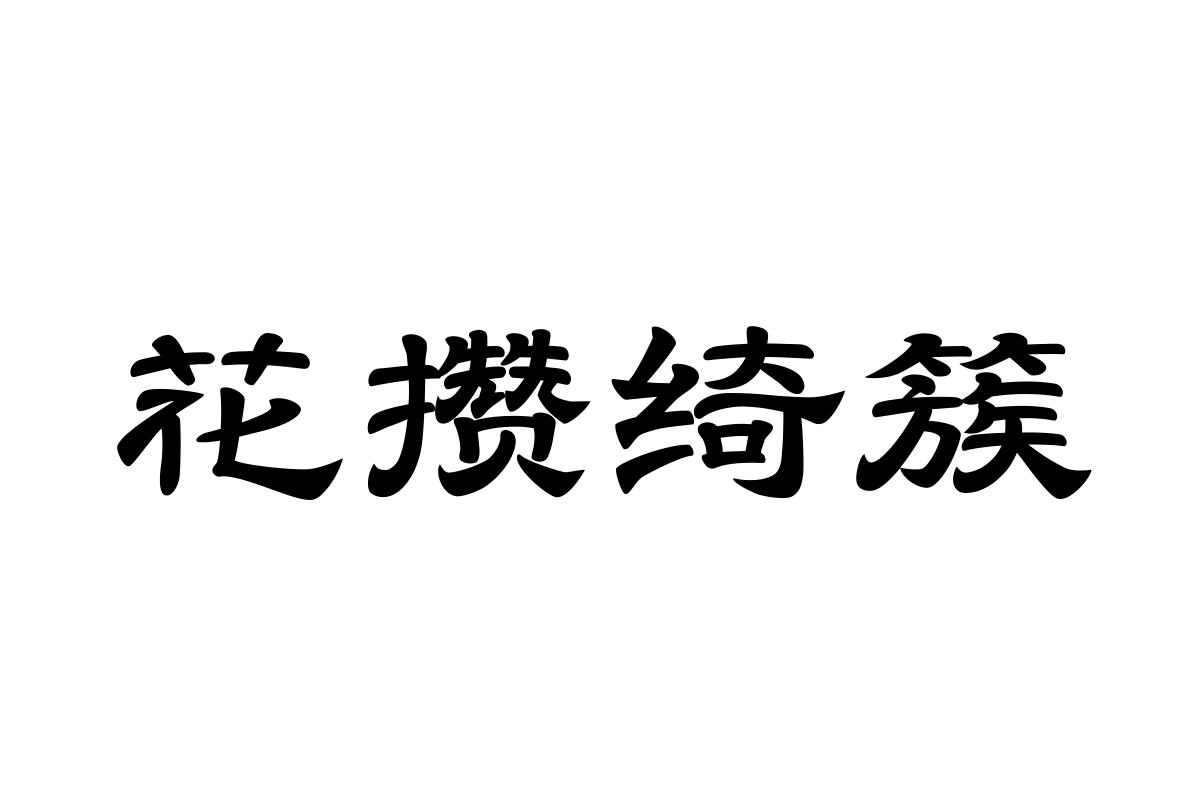
汉仪润隶是一款具有现代感和优雅风格的中文字体,它以圆润的笔画、清晰的结构以及丰富的细节表现而著称。这款字体适合用于需要强调文字美感和艺术气息的设计项目,如广告、包装、杂志、网页等。
汉仪润隶的特点包括:
1. 圆润的笔画:汉仪润隶的笔画呈现出一种柔和的弧度,使得文字看起来更加亲切和易于阅读。
2. 清晰的结构:该字体的结构严谨,每个字符都保持了良好的比例和平衡,使得整体设计看起来和谐统一。
3. 丰富的细节:汉仪润隶在细节上做了充分的处理,如字框、笔画连接处等都进行了精心设计,使得整个字体看起来更加精致和有层次感。
4. 适应性强:这款字体适用于多种场景,无论是正式的商业文档还是轻松的社交媒体内容,都能展现出其独特的魅力。
总之,汉仪润隶是一款非常适合现代设计需求的中文字体,无论是用于品牌建设还是个人作品,都能为设计增添一份独特的艺术韵味。